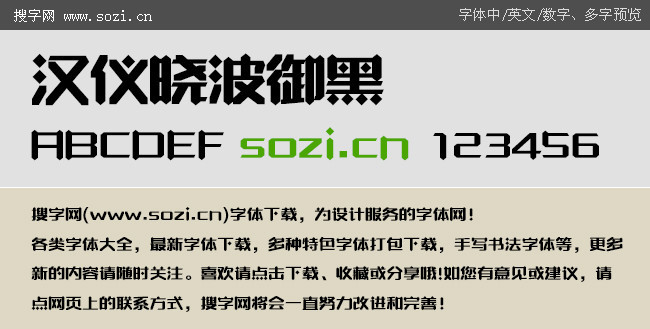
漢儀曉波御黑
搜字網(wǎng)給大家提供一款漢儀曉波御黑中文字體下載,漢儀曉波御黑字體是一款把幾何圖形融入到字體設(shè)計框架中的特色中文樣式。適用于畫冊設(shè)計、海報設(shè)計、包裝設(shè)計等場合使用。(本字體為個人非商用版,如需要商用請聯(lián)系漢儀公司購買版權(quán))